2023 年 29 种最佳游戏字体(免费和付费)
已发表: 2023-04-12寻找最好的游戏字体可能具有挑战性; 那里有很多选择。 正确的字体可以决定游戏的成功与失败。
正确的字体可以为您的游戏带来独特的触感,使其脱颖而出。 从经典的块状字体到优雅的脚本字体,游戏字体可满足各种需求。
这里有一些最好的游戏字体,以及如何为您的项目选择合适的字体。 基本上,我们将讨论字体样式、可读性、兼容性等。所以,让我们开始寻找完美的游戏字体吧!
最佳高级游戏字体
如果您寻找经典的衬线字体,或者如果您更喜欢现代的无衬线字体,那么在高级字体方面您会发现很多选择。 一个好的字体肯定会提升玩家在这类游戏中的体验。
履带式
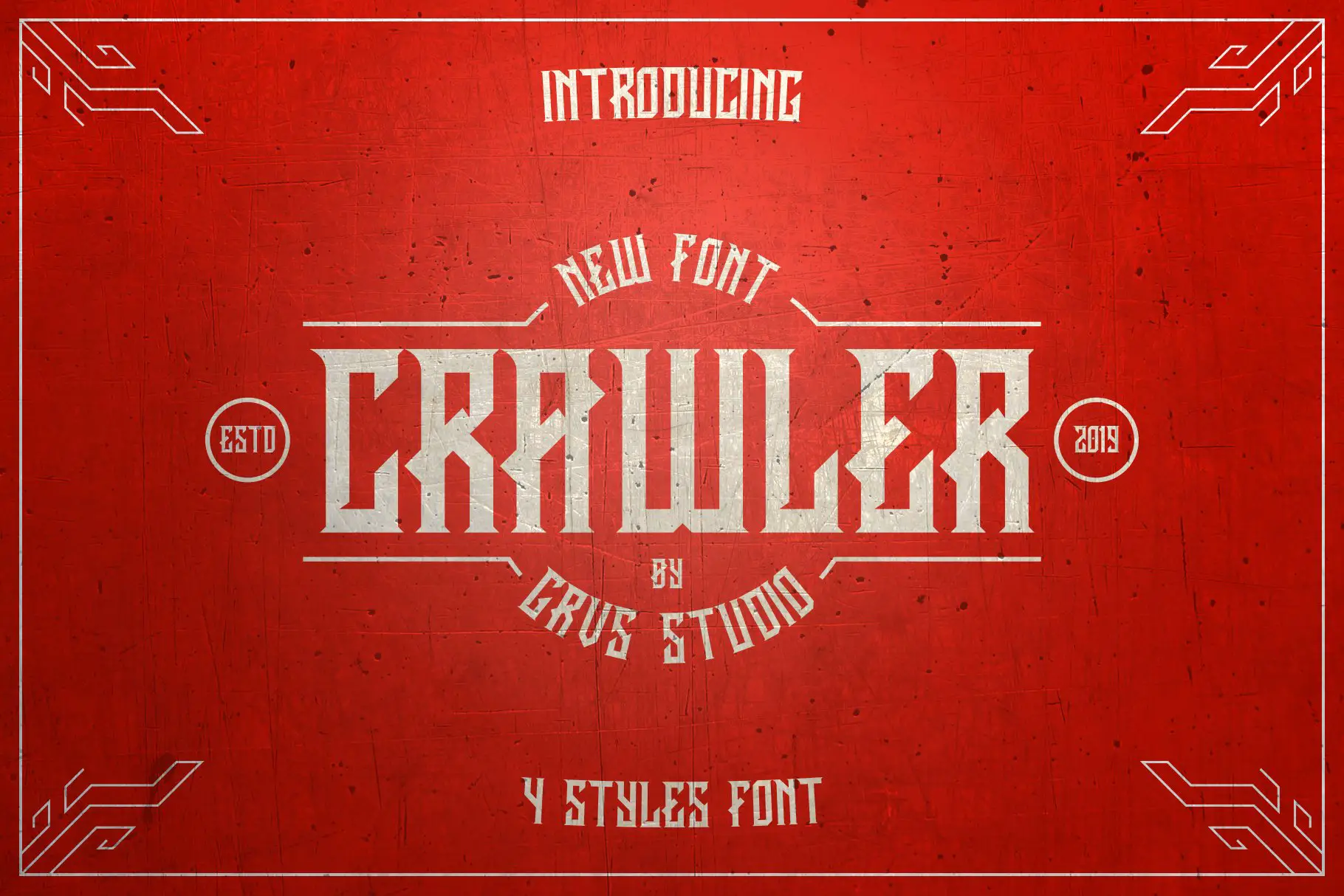
Crawler 是一种现代字体和吉祥物标志模板,非常适合寻找独特字体的平面设计师。 它包括四种字体样式、一个具有四种颜色变体的吉祥物徽标模板、四种可编辑字体和一个 Microsoft Word 教程。
吉祥物标志模板也是对 Crawler 的一个很好的补充。 它提供四种颜色变体,这意味着您可以轻松自定义它以匹配您项目的品牌。 此外,该模板还带有四种可编辑字体,因此您可以根据需要进行进一步的更改。 为了帮助您立即开始,该模板包含一个 Microsoft Word 教程。
总之,Crawler 是一款很棒的字体和吉祥物徽标模板,具有许多自定义选项,非常适合寻求独特之处的平面设计师。 另外,随附的教程使它变得更加容易!
GRVS Scythrone
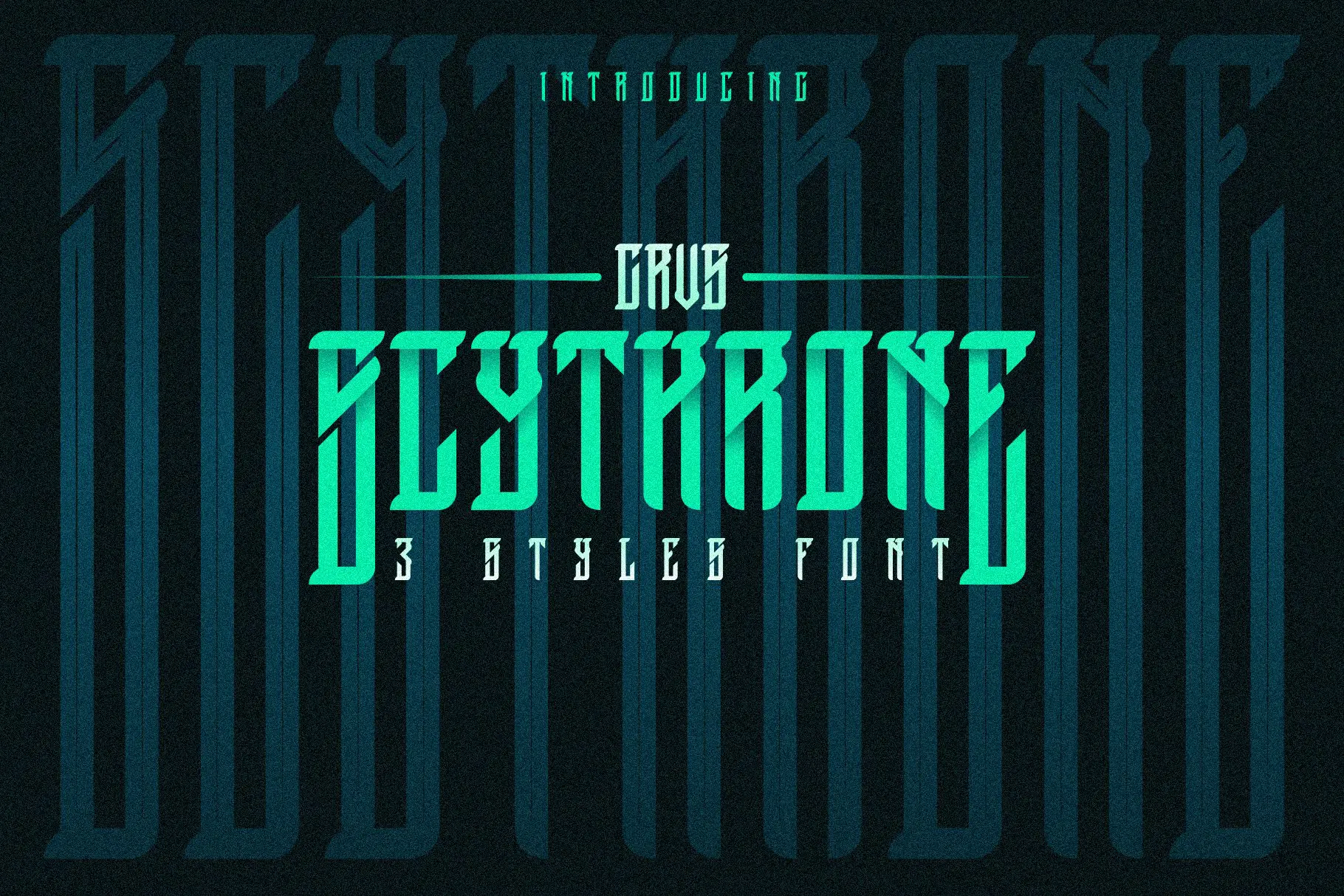
GRVS Scythrone 是想要为其项目打造时尚外观的平面设计师的绝佳选择。 凭借其现代风格和多功能格式,这种字体一定会让您的作品在竞争中脱颖而出。
字体中包含的矢量文件可以轻松创建不同的变体。 无论您是为网络创建设计还是打印,您都可以轻松编辑矢量以获得完全自定义的外观。 凭借其多种样式选项,您可以使用该字体在整个项目中创建一个有凝聚力的外观。
电子游戏
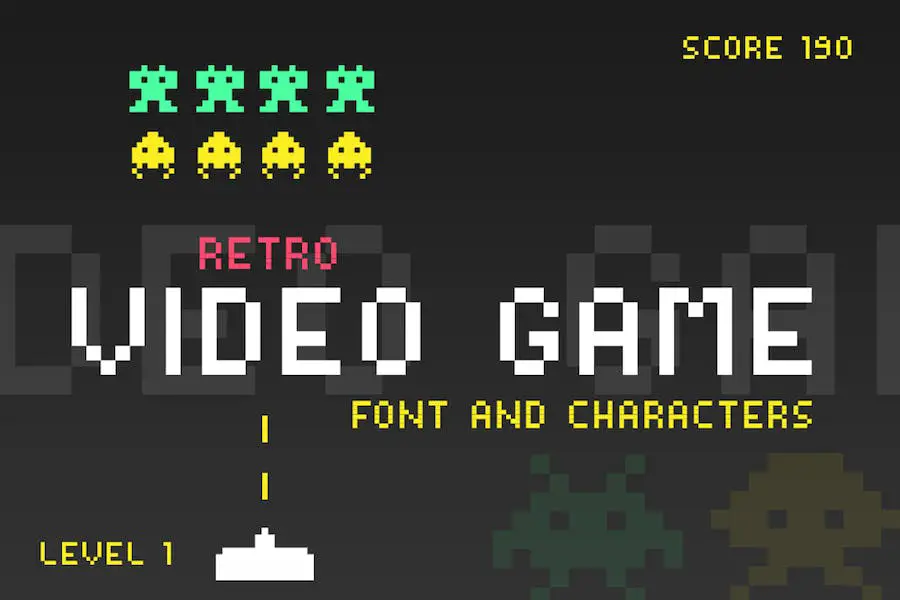
新字体 Video Game 通过 17 个像素化火星人展现了过去的风采,非常适合创建复古炫酷的设计。
使用大写字母,您可以展示每个标志符号,而小写字母则为您的设计增添一些额外的个性和风格。 您可以使用 Video Games 字体为任何事物添加独特的风格,或者只是为了捕捉一些老式的氛围。
凯撒电竞
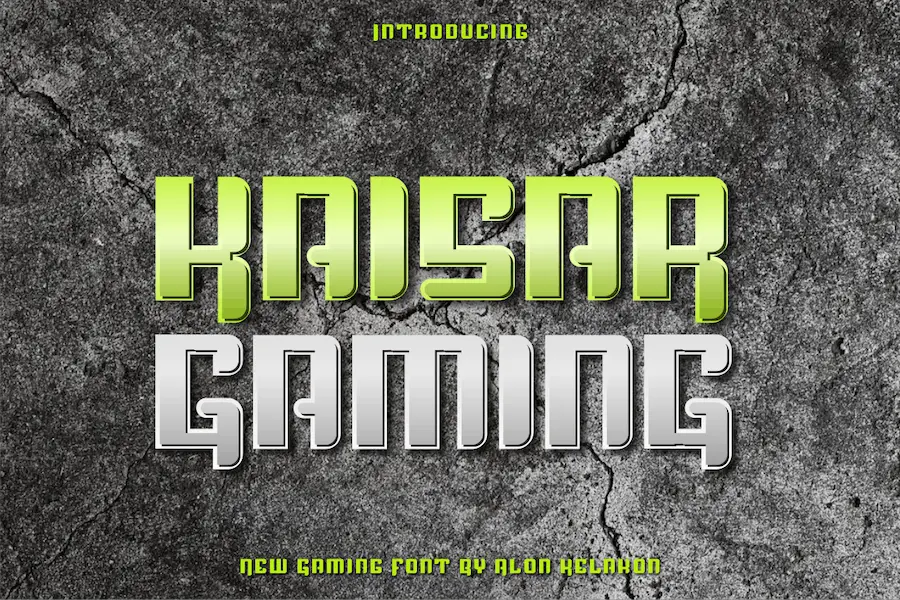
Kaisar Gaming 是一种独特的字体,非常适合您可能想到的任何设计项目。 无论是标签、服装、电影场景、海报、电影标题、演出、专辑封面、徽标等等,Kaisar Gaming 都能胜任。 它同时具有 OTF 和 TTF 文件格式,以及 WOFF 兼容性,因此您可以确定您正在处理的任何项目都可以使用此字体。
Kaisar Gaming 的美妙之处在于它的多功能性。 它具有多种用途,从为衣物贴标签到创建徽标再到设计电影片名。 无论您将其用于什么用途,它看起来都很棒,并使任何设计项目脱颖而出。 字体无论大小看起来都很棒,这意味着您永远不必担心文本的大小看起来不合适。
您几乎可以使用 Kaisar Gaming 进行任何操作。 它用途广泛,易于使用,并因其独特的风格而脱颖而出。 如果你想要一种时尚但易于使用的字体,你可以将它用于 Adobe 游戏字体。
游戏结束
GameOver 字体受经典视频游戏的启发并采用几何形状制作而成,将复古风格与现代设计融为一体。
除了具有建构主义的感觉外,它还散发出一种复古的氛围,过去的任何人都会欣赏。 此外,它很简单,因此在任何环境下都易于阅读,非常适合商务人士或任何想要与众不同和时尚的人。
由于其多功能性,将 GameOver 用于海报、徽标等非常容易。 它具有广泛的字重范围,能够处理大文本和小文本,因此您不必牺牲可读性来发表声明。 作为一个额外的好处,它也是可访问的,所以任何人都可以使用它。
好游戏
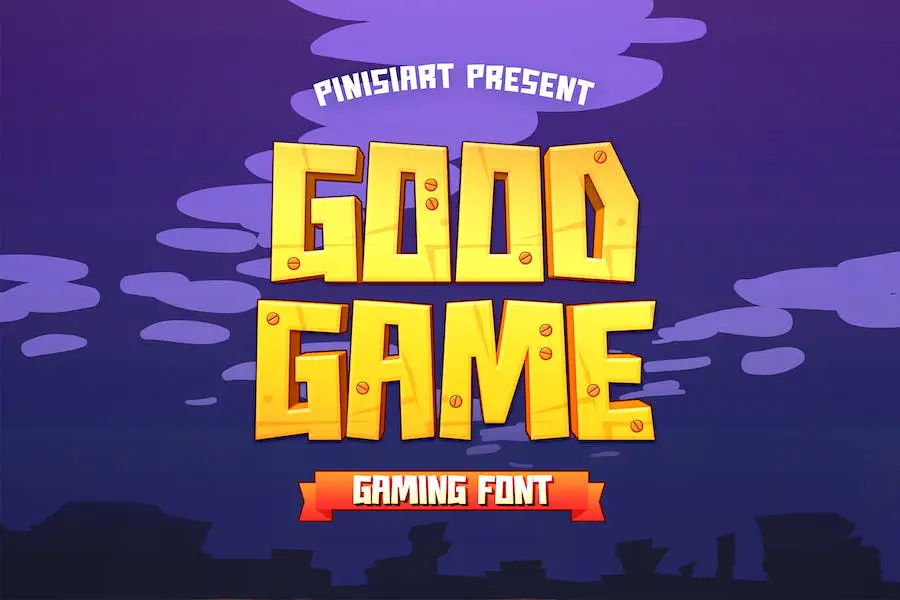
任何想要为他们的项目增添一些天赋和个性的人都可以使用 Good Game。 它易于使用和理解,并且有许多可用的自定义选项,因此它非常通用。
这是一种有趣的、面向游戏的字体,非常适合与元宇宙、未来和技术相关的项目。 它非常适合书籍、在线游戏、海报、生日邀请函、YouTube 封面、YouTube 缩略图、社交媒体页面封面等,因为它很有趣并且以游戏为导向。
该字体还带有一堆特殊字符和符号,有助于为您的项目增添一些个性。 无论您是创建徽标还是海报,Good Game 都会确保它脱颖而出。 最重要的是,该字体是免费的,因此无需担心倾家荡产!
CLOWSH电子竞技
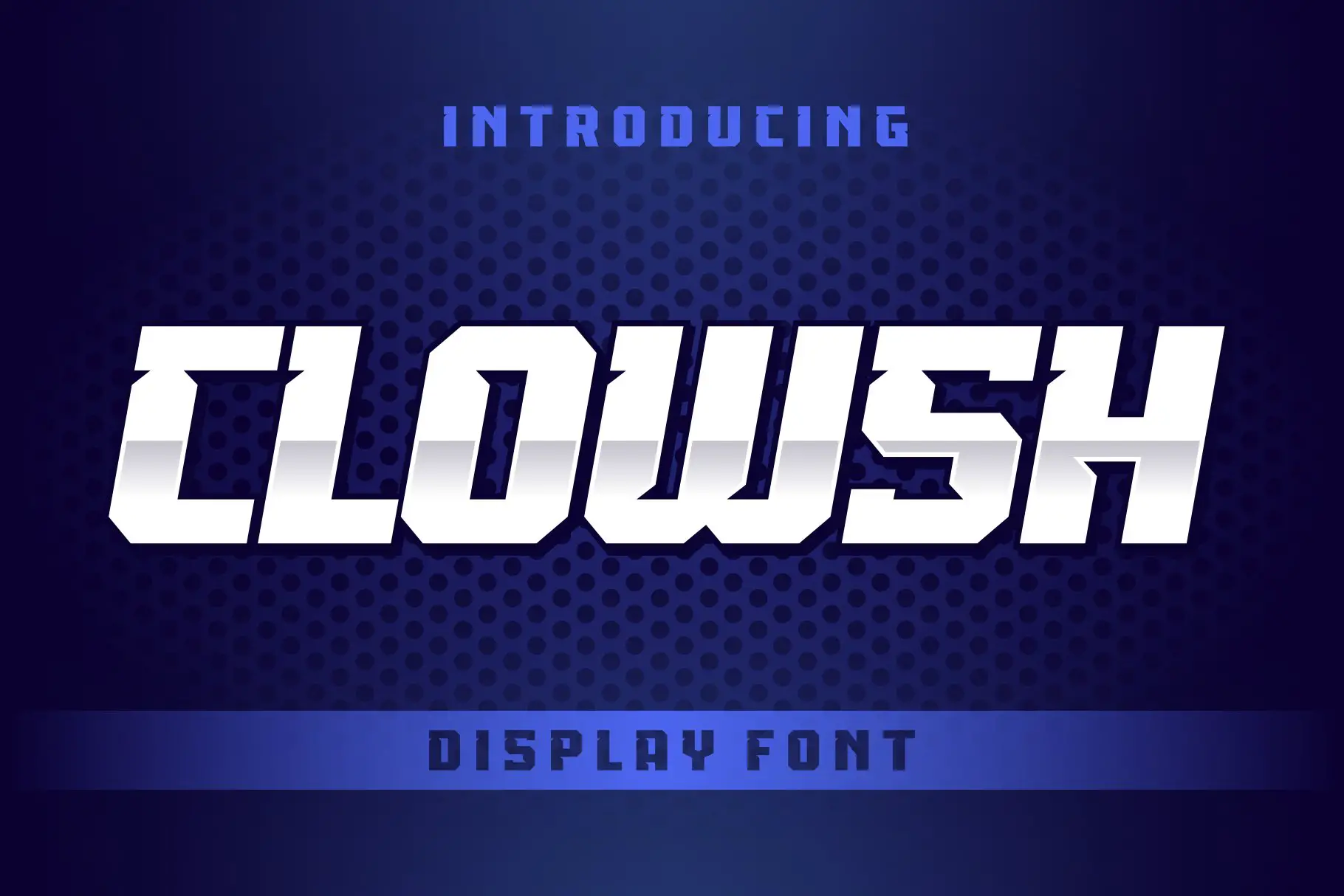
CLOWSH ESPORT 是一个革命性的游戏字体集合,非常适合电子竞技徽标设计、流媒体和社交媒体。 CLOWSH ESPORT 具有大写和小写字符、数字、标点符号和符号,提供多语言支持,并与 Mac 和 Windows 操作系统以及所有主要设计应用程序(如 Photoshop 和 Illustrator)兼容。
您可以使用 CLOWSH ESPORT,因为它超级大胆、锐利,并且适合任何游戏主题。 此外,它非常适合 Figma,因为它支持游戏字体。
体育玩家
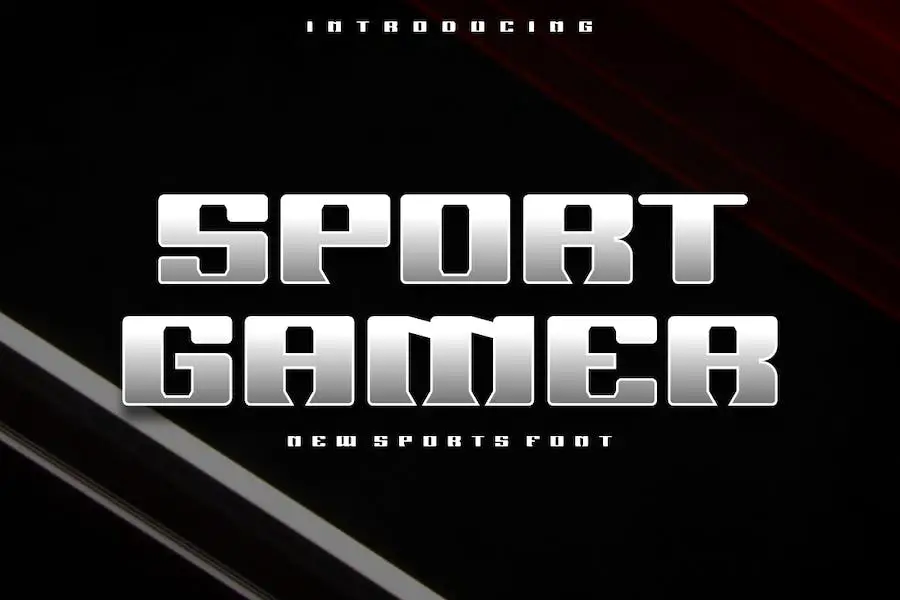
Sport Gamer Font 是一种大胆而现代的显示字体,非常适合任何项目。 它非常适合徽标、T 恤印花、电子竞技等。 该字体在各种环境中脱颖而出。
它结合了独特的设计和易于使用的属性,使 Sports Gamer Font 成为任何想要创造令人兴奋的产品的人的绝佳选择。 除了易于使用之外,Sports Gamer Font 还具有多种字符,可帮助您创建各种设计。!
运动赞
Sportzan 是一种大胆而强大的字体,可为任何项目带来欢快和运动的能量。 无论您是在制作海报、球衣、标语还是任何其他类型的设计作品,这种字体都能确保您的信息脱颖而出。
它的尖角赋予它特别强烈的外观,有助于强调您想要传达的任何信息。 Sportzan 是运动相关项目的完美选择,可为任何设计带来大胆而充满活力的精神。 另外,它是文字游戏字体的理想选择。
高级游戏
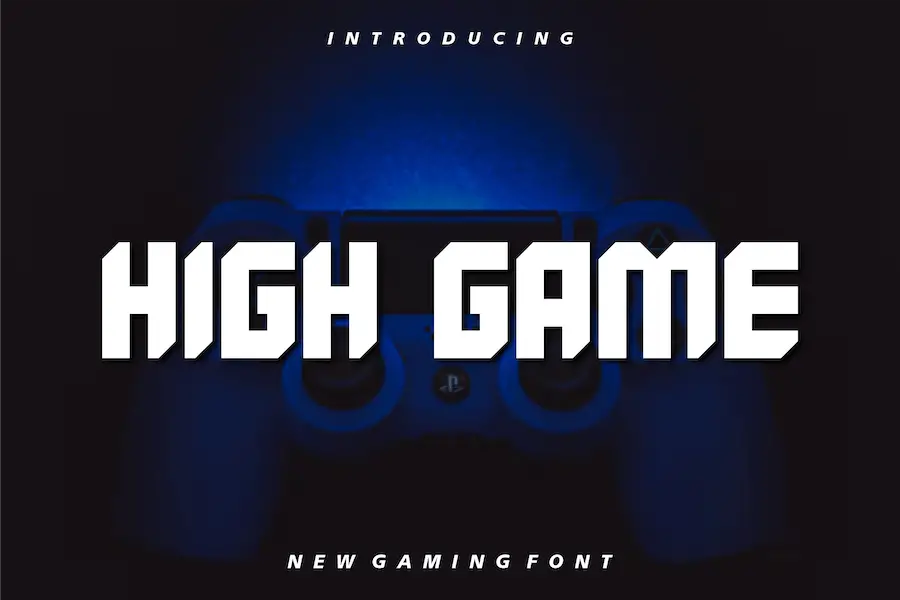
High Game Font 是一种大胆而现代的显示字体,是任何品牌项目的绝佳选择。 除了其真实的感觉,它在很多环境中都脱颖而出,从标志设计到电子竞技。 它具有易于阅读的强烈字符形状,并且具有独特但仍然经典的风格。 High Game Font 非常适合制作徽标或引人注目的 T 恤设计。
例如,如果您需要一种可以轻松调整大小的字体,就是这样。 此外,它的易读性和多功能性使其非常适合印刷和数字使用。
十一健身
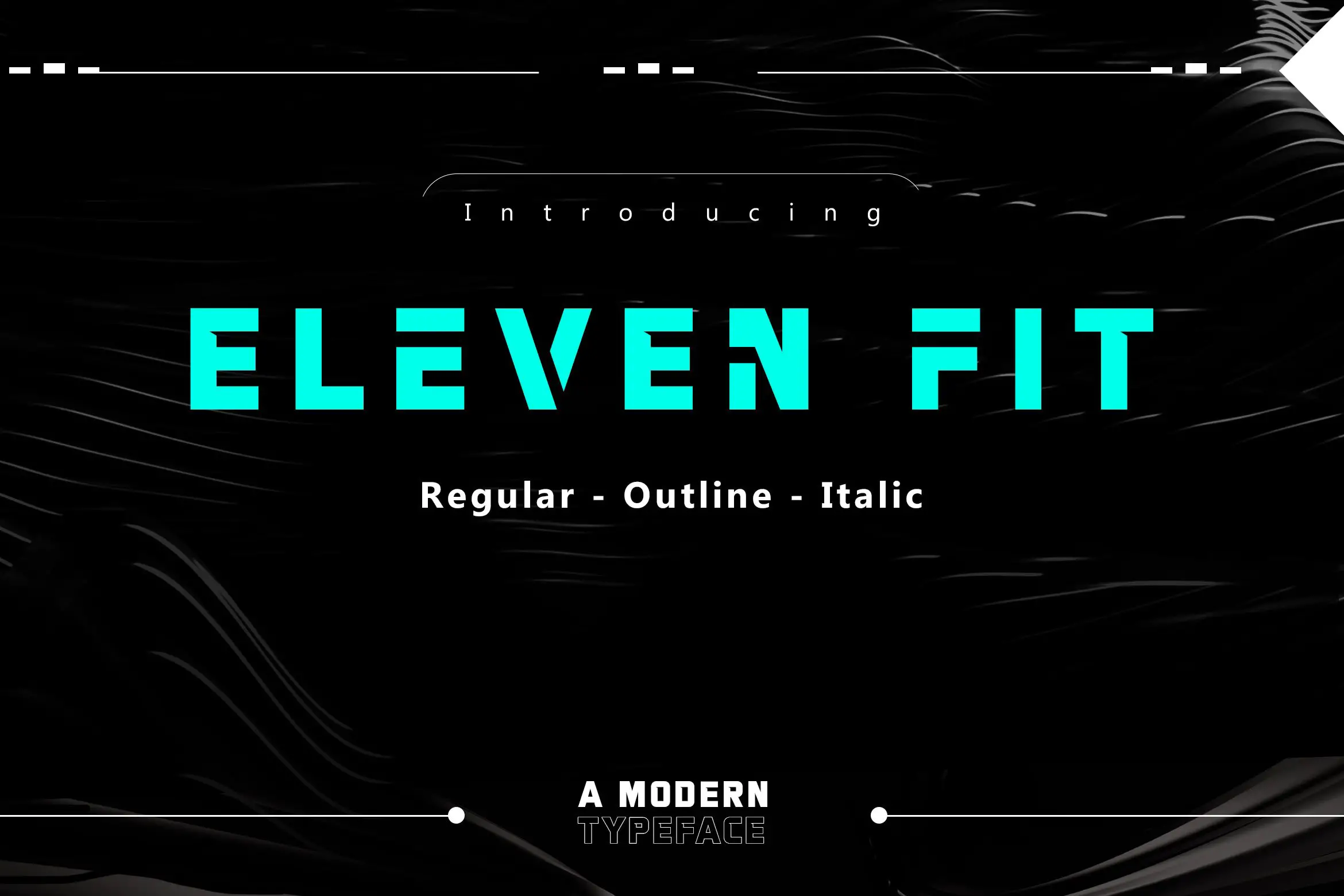
ElevenFit 字体是一款受运动启发的字体,专为想要个性化字体的平面设计师而设计。 它包括大写和小写字符、标点字符、数字和多语言支持。 小写字符也出现在一堆文体替代品中。
您可以将 ElevenFit 用作品牌和徽标设计工具。 其独特的风格将使您的项目看起来强大而专业。 您还可以使用它来设计海报和网页图形。
总的来说,如果您正在寻找一种现代、运动的字体,ElevenFit 是一个不错的选择。 凭借其标点符号和多语言支持,它为您的项目提供了专业的感觉,是电路游戏字体的理想选择。
民族风
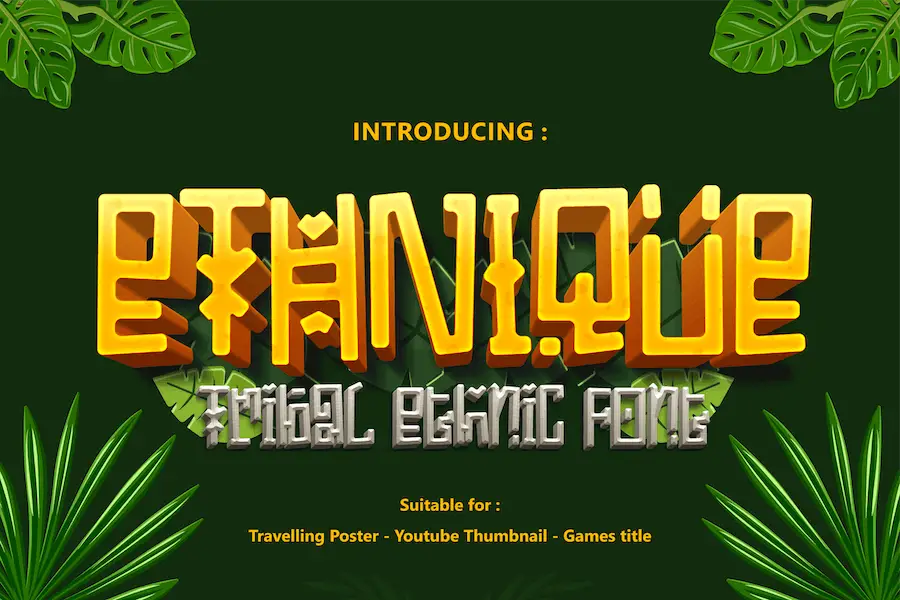
Ethnique 是一种独特的创新字体,灵感来自古代玛雅人和阿兹特克部落的文字。 这种字体古怪的形状和线条给人一种真实的部落感觉,任何游戏或图形设计师都会为在他们的作品中出现而感到自豪。
这种字体在在线游戏、海报、电影标题、快餐菜单、杂志、YouTube 封面、缩略图、社交媒体页面封面和冒险传单上看起来很棒。 Ethnique 具有复古气息,使其从更现代的字体中脱颖而出,并赋予任何项目独特的外观。
开发者
对于那些需要在任何项目中使用有吸引力、功能强大的字体的人来说,Developer 是一个不错的选择。 凭借其时尚、多功能的设计、高级排版功能和广泛的语言支持,它非常适合任何想要创造令人惊叹的视觉效果(如纹身游戏字体)的设计师。
这种字体非常通用,因此您可以使用它来制作能够吸引人们注意力的出色设计。 其权威的外观将使任何设计看起来专业而强大。 这种字体具有锋利的边缘和平滑的曲线,看起来很棒,并且具有独特的字母和符号,使其更加出色。
国王电竞
King Gaming 字体以其俏皮、现代的风格在人群中脱颖而出,无论是用于电影、游戏还是冒险主题的设计工作。
这种字体具有独特的风格,融合了经典字体和现代风格。 虽然强大而大胆,但它具有微妙的优雅,使其经久不衰。
除了出色的可读性,King Gaming 凭借其多功能的设计和广泛的用途,必将成为设计师的必备字体。
海洛芬
您可以将 Helofone 用于数字和印刷设计,无论您使用什么设备或平台,它看起来都很棒。 字母清晰易读,因此您可以在较小的尺寸下使用它而不会失去清晰度。 它还带有备用字符,因此您可以按照自己的想法自定义设计,例如 Canva 的游戏字体。
Helofone 也非常易于使用。 您无需成为专业的平面设计师即可充分利用它——即使是初学者也可以快速轻松地创建令人惊叹的设计。 该字体有 TrueType 和 OpenType 两种格式,因此您可以将它与几乎所有现代软件一起使用。
玩家站
Gamer Station 字体非常适合为任何设计带来额外的生命力。 它用途广泛且质量上乘,因此您可以将其用于任何项目。 此外,您可以使用它来制作真正独特和富有创意的东西,因为它易于阅读并且带有许多替代字符。
这种字体非常适合让设计更具吸引力和乐趣。 它旨在激发俏皮活泼的卡通风格排版。 具有良好的美感,适用于书籍封面、儿童读物、漫画、海报、包装、商品、徽标等。
除了您在游戏字体中期望的所有字符外,还有一些额外的特殊字符。 使用这种字体,您可以为您的设计添加很多个性,因为它易于阅读并且在任何背景下看起来都很棒。 还有很多替代角色,所以你可以把它变成你自己的。
格罗泽尔
没有什么比 Grozel 更有趣、更酷的显示字体了,它非常适合徽标、品牌、杂志封面、社交媒体帖子、广告、专辑封面等。
结合粗线和细线,形成具有不规则形状的视觉醒目的字体,使其具有突出的前卫美感。
争吵者
Brawler 是一种专为视频游戏项目创建的独特字体。 它非常适合游戏缩略图、电子竞技徽标、Twitch 流、播客封面、漫画书、食物菜单等。 凭借其俏皮、友好和诱人的设计,Brawler 一定会让您的设计脱颖而出。
泰坦
我们正在推出 Titan 字体和吉祥物徽标模板,这是一种多功能字体和徽标模板,非常适合想要与众不同的平面设计师。 它带有三种不同的字体样式,因此您有很多选择。
它易于使用,而且看起来很专业。 无论您是创建徽标、海报还是宣传材料,Titan 字体都将帮助您做出引人注目的声明。 凭借其干净、大胆的线条和流畅的曲线,Titan 一定会为您的图形增添一些优势。
经常问的问题
游戏字体是一种专门设计用于视频游戏的字体。 它考虑到了大多数游戏设计的像素限制,这意味着它比其他字体具有更高的易读性,同时仍然传达出一种动作感、兴奋感或强度感。
自从街机游戏在 80 年代流行以来,游戏字体就一直存在。 随着时间的推移,它们得到了改进和增强,使它们更加清晰易读,因此玩家可以阅读说明。 这些基本字体已通过更现代的功能得到增强,例如粗体、斜体和字体粗细。
您应该选择一种在屏幕和纸上看起来都不错的字体,尤其是当您的游戏需要玩家快速阅读时。
凭借适合视频游戏的独特功能,游戏字体从传统字体中脱颖而出。 夸张的字体、大胆的线条和独特的形状吸引玩家注意文字并传达游戏试图表达的任何信息。 此外,游戏字体可以为您的游戏设计增添一点风情。
结论
以下是我们为游戏找到的一些最佳字体,我们比较了各种字体,包括经典字体和现代字体,以搜索看起来最好的字体。